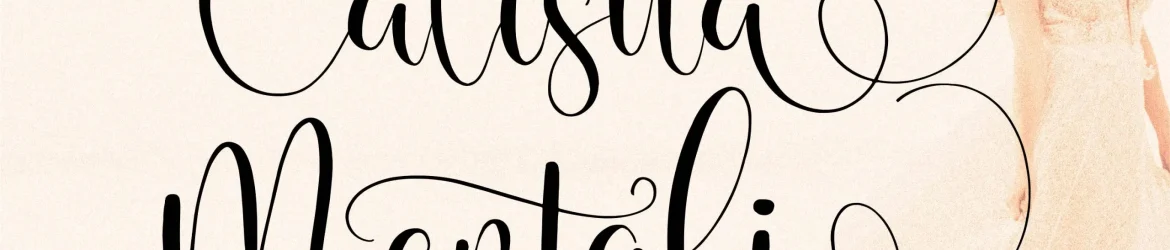
Calistta Mentali Font – Download Grátis
A Calistta Mentali Font é uma elegante tipografia romântica ideal para projetos variados que buscam incorporar um toque delicado e sofisticado ao design, tornando-os ainda mais atraentes e memoráveis. Sua versatilidade permite usá-la em uma ampla gama de aplicativos, desde criação de logomarcas e embalagens para produtos até cartões de visita e convites. Seja no campo da arquitetura, design gráfico ou arte digital, a Calistta Mentali traz um toque autêntico e delicado que certamente impressionará seus clientes e criadores. Essa fonte é perfeita para aqueles projetos em que você deseja adicionar um toque romântico ao seu design, seja ele uma capa de livro ilustrada ou o texto dos seus cartões personalizados. A Calistta Mentali é a escolha ideal para tornar suas criações ainda mais singulares e memoráveis. Sua forma curvilínea e delicada oferece uma sensação romântica que se encaixa perfeitamente em qualquer projeto, tornando-a uma fonte imperdível para qualquer designer ou artista gráfico.